Phông chữ mặc định của Office từng là Times New Roman, đã được thay thế bằng Cailibri vào năm 2007. Tuy nhiên, Microsoft tin rằng đã đến lúc để sửa đổi và nhóm thiết kế của Microsoft đang cần người dùng bỏ phiếu để chọn ra một font chữ mặc định mới từ năm lựa chọn khác nhau cho các ứng dụng văn phòng.
Microsoft hiếm khi sửa đổi font chữ mặc định trong các ứng dụng văn phòng của mình. Lần gần đây nhất là vào năm 2007, khi Calibri thay thế Times New Roman. 14 năm đã trôi qua và Microsoft muốn làm điều đó một lần nữa, nhưng lần này là với sự giúp đỡ của người dùng Microsoft 365. Trong số 5 phông chữ chỉnh sửa tùy ý mà Microsoft cung cấp, người dùng phải chọn ra một font chữ và cho dù phông chữ yêu thích của bạn không giành được chiến thắng, Microsoft sẽ giữ lại tất cả trong các ứng dụng Microsoft 365.
Microsoft Office thêm Font chữ mặc định mới
Năm phông chữ mới bao gồm Tenorite, Bierstadt, Skeena, Seaford và Grandview. Đội ngũ thiết kế của Microsoft sẽ đánh giá các phông chữ trong vài tháng tới cùng với người dùng Microsoft 365 và mong họ đưa ra ý kiến của mình thông qua mạng xã hội sau khi thử nghiệm.
Các nhà thiết kế của font chữ Tenorite nói rằng font chữ của họ theo kiểu “sans-serif” (tức là kiểu phông chữ không có chân), nhưng “thân thiện hơn”. Nó bao gồm các yếu tố như dấu trọng tâm, dấu chấm câu đậm, sẽ giúp bạn dễ đọc hơn trên màn hình nhỏ, cũng như các ký tự rộng và rõ ràng hơn.
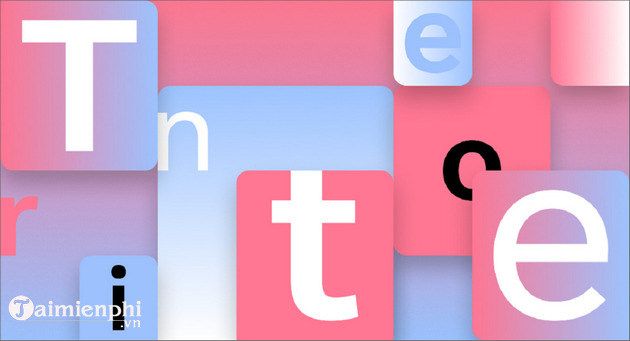
Font chữ Bierstadt áp dụng một phong cách hiện đại, “lấy cảm hứng từ kiểu chữ Thụy Sĩ giữa thế kỷ 20”. Các ký tự được thiết kế đơn giản và rõ ràng, với những đường cong mạnh mẽ, tương tự như những gì chúng ta tìm thấy trong font Helvetica.
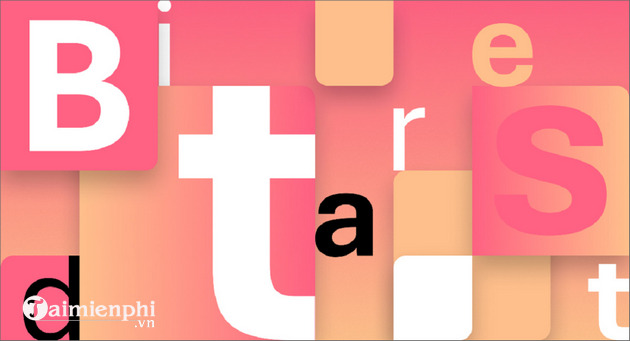
Có thể nói rằng, Skeena là font chữ độc đáo nhất. Dựa trên nhiều xu hướng thiết kế phông chữ trong lịch sử, các nhà thiết kế tạo ra một phông chữ với các ký tự có độ dày khác nhau. Mặc dù phù hợp hơn với các văn bản dài, nhưng nó cũng là lựa chọn tuyệt vời cho các phần văn bản ngắn như bảng, bản trình bày và tài liệu quảng cáo.
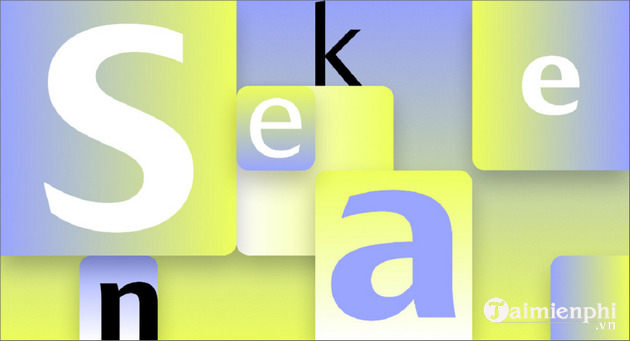
Seaford là kiểu chữ có chân (serif) mang phong cách cổ điển nên mang lại cảm giác quen thuộc cho hầu hết mọi người. Với các nét không đối xứng và các ký tự đặc biệt, Seaford tạo cảm giác thoải mái khi đọc nội dung được định dạng với font chữ này.
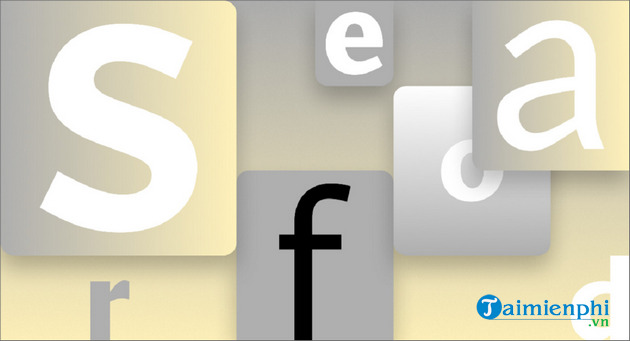
Cuối cùng, Grandview là một kiểu chữ “sans-serif” (không chân) khác có nguồn gốc từ biển báo đường bộ và đường sắt của Đức. Điều đó có nghĩa là kiểu chữ này dễ nhìn và nhà thiết kế đã làm một số điều chỉnh nhỏ để tạo sự thoải mái khi đọc.